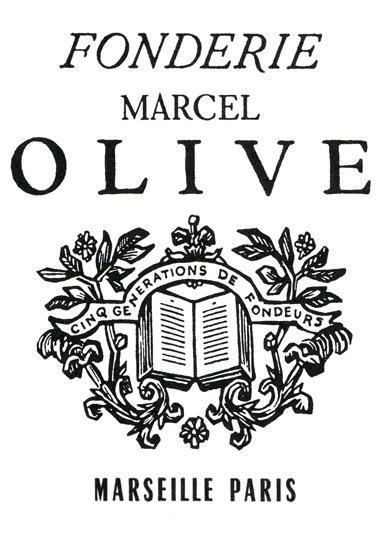
• Land: Frankreich
• Ort: Marseille
• Status: nicht mehr aktiv
Die Fonderie Olive war eine Schriftgießerei in Marseille, die Mitte des 20. Jahrhunderts vor allem für ihre Schriften von Roger Excoffon Bekanntheit erlangte. Ende der 1970er-Jahre wurde das Unternehmen vom mittlerweile 66-jährigen Marcel Olive verkauft. Die Bleisatzmaterialien gingen an das Schweizer Unternehmen Haas. Daneben wurden jedoch auch Lizenzverträge für die Schriften mit anderen Herstellern abgeschlossen.